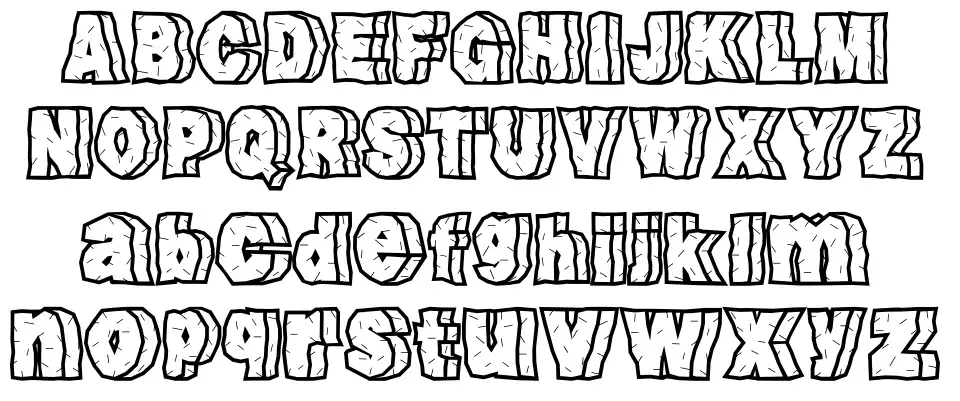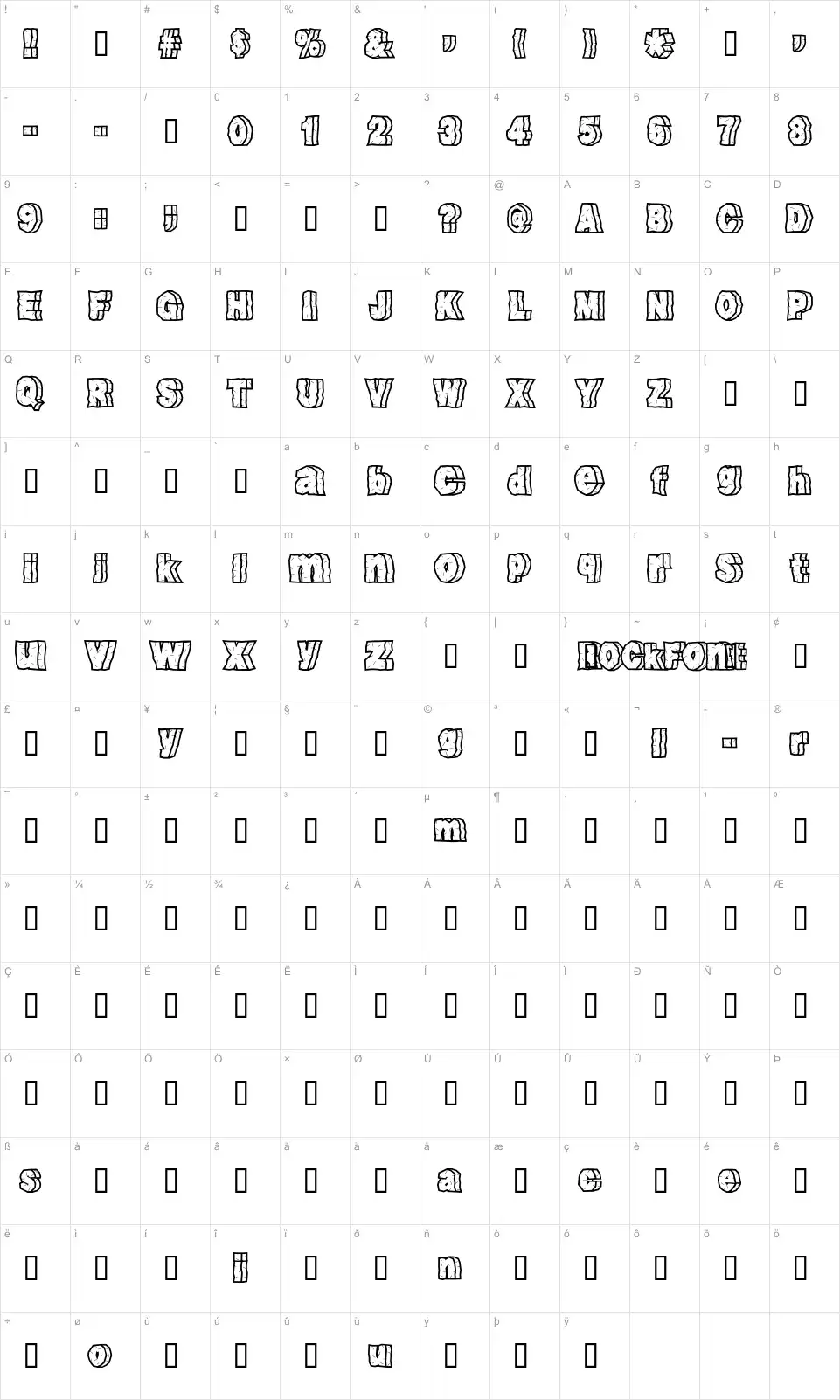
Rock Font – Download Grátis
A fonte Rock Font, criada pela Gaut Fonts, é uma escolha perfeita para adicionar um toque único e divertido a seus projetos gráficos. Se você está buscando um fonte com um estilo fancy e cartunizado, a Rock Font é uma ótima opção. Se você estiver procurando por uma fonte que traz um ar divertido e descontraído aos seus materiais, a Rock Font é perfeita para você. Licenciada para uso pessoal, a fonte Rock Font é disponível em formato TTF, que permite que você use e personalize conforme desejar. Adicionada ao nosso catálogo em 12 de julho de 2022, ela já foi baixada mais de 2636 vezes. Com seu tamanho de apenas 41 KB, Rock Font é uma fonte leve e versátil que se destaca em qualquer projeto, especialmente quando combinada com seu estilo fancy e cartunizado. Para que você possa experimentar a Rock Font em um projeto antes de utilizá-la, você pode baixá-la ou gerar um preview de texto personalizado online. Este processo online permite que você veja como a fonte se assemelha em seus materiais sem precisar de tempo adicional para aplicá-la. Com seu website do designer acessível em http://moorstation.org/typoasis/designers/gaut, você pode explorar mais projetos e fontes criados pela Gaut Fonts para encontrar novas inspirações. A fonte Rock Font é uma excelente escolha para quem procura um touch divertido e único para seus projetos gráficos.